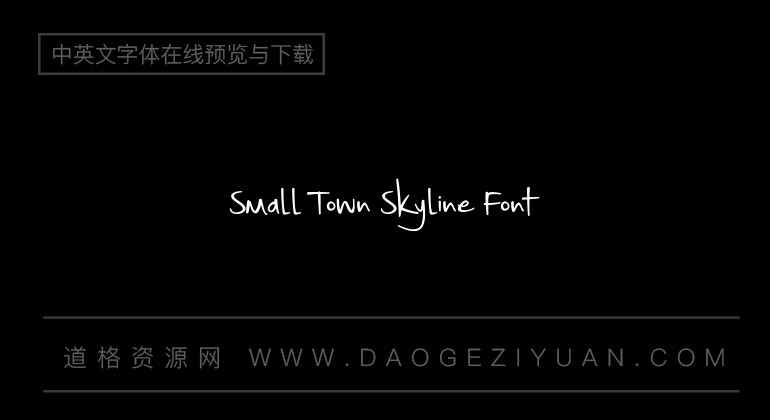
Small Town Skyline Font 是一种现代化的手写字体,具有创新的风格和个性化的设计元素。它的字体形状流畅,笔画变化多样,字母之间的间距也很合理,使得整体效果非常和谐。 这种字体适用于许多设计场景,特别是需要突出手写风格的项目。例如,它可以用于海报设计、印刷品、品牌标识、包装设计、网站设计等等。这种字体可以轻松地传达出温馨、友善、亲切、自然等多种情感和感觉,为设计带来更多的生命力和个性化。内容介绍
Small Town Skyline Font是一款非常不错的手写艺术字体,具有很好的视觉感,适合于文化类的宣传设计、商业类品牌的广告和产品包装设计以及个性化文字排版等较多场景。